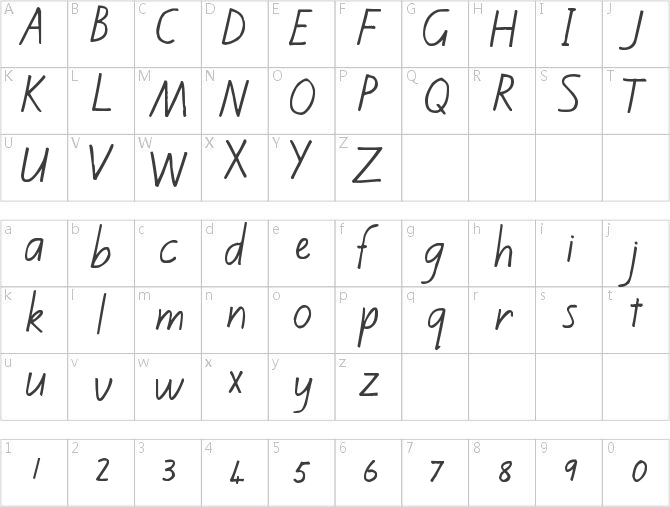
字體名稱: kiwisch
kiwischoolhandwritingregular
kiwischoolhandwritingregular字體字庫是一款讓人賞心悅目、百看不厭的英文字體,適合各類廣告和產品包裝設計應用,字體大小0.02MB,格式為ttf字體,上傳用戶是素年錦時,作者/版權方為未知